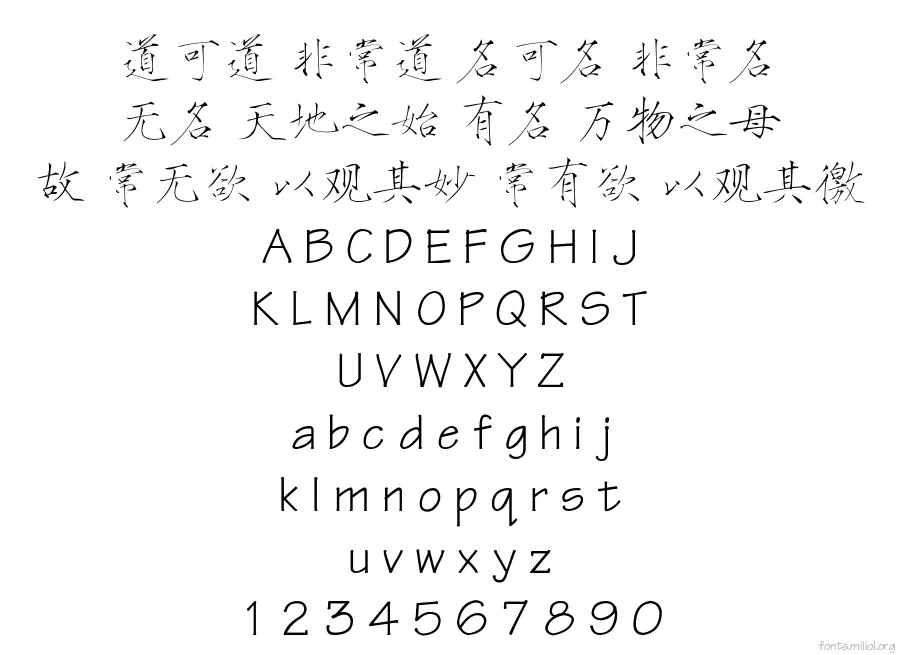
方正瘦金书简体 (FZShouJinShu-S10S) (FZSJSJW--GB1-0) 字体下载
## 方正瘦金书简体:数字时代的宋徽宗遗韵
方正瘦金书简体(FZShouJinShu-S10S)作为一款基于宋徽宗瘦金体风格设计的现代字体,完美融合了传统书法艺术与数字排版技术。这款字体以"FZSJSJW--GB1-0"为编码标识,在保持瘦金体原有艺术特征的同时,通过精密的数字化处理,使其完全符合GB2312-80字符集标准,确保在现代电子设备上的完美呈现。
瘦金体特有的"铁画银钩"笔法在方正瘦金书简体中得到忠实再现,横画收笔处的顿挫、竖画末端的锋芒都经过精心设计。字体结构保留了原作的瘦劲挺拔,笔画间的疏密对比强化了视觉张力,使每个字符都如微型艺术品般精致。特别值得注意的是,设计师在数字化过程中充分考虑了屏幕显示特性,通过笔画粗细的微妙调整,解决了传统书法字体在小字号显示时的识别难题。
这款字体的开发历时三年,设计团队对宋代《秾芳诗帖》等瘦金体代表作进行了上千小时的临摹研究,最终实现了书法韵味与印刷功能的平衡。如今,方正瘦金书简体已成为设计师钟爱的文化符号载体,在书籍装帧、品牌设计、文化宣传等领域展现着独特的东方美学魅力。
方正瘦金书简体 字体映射图